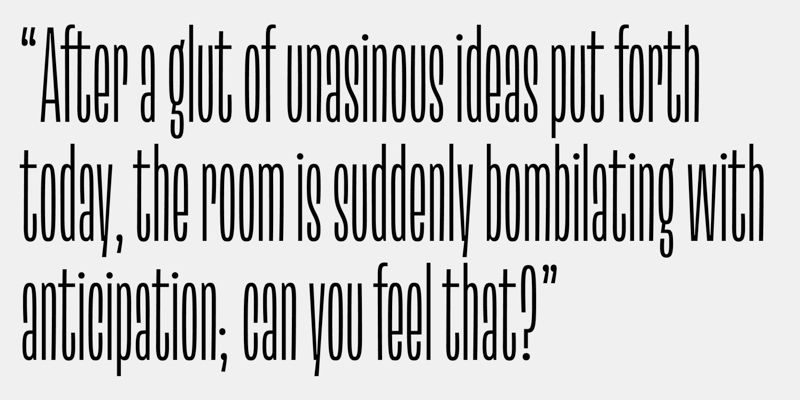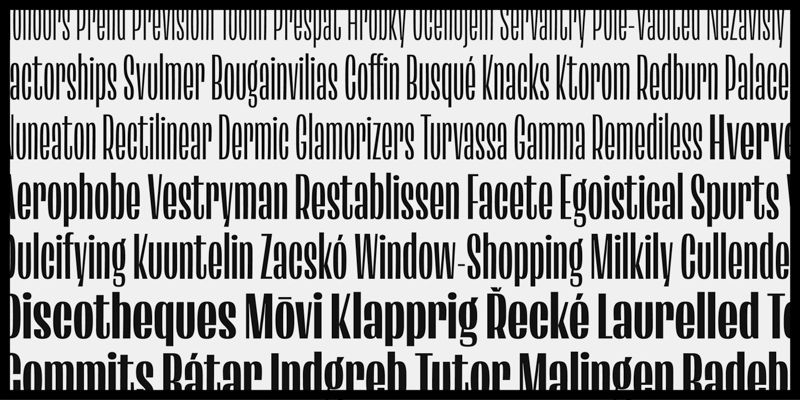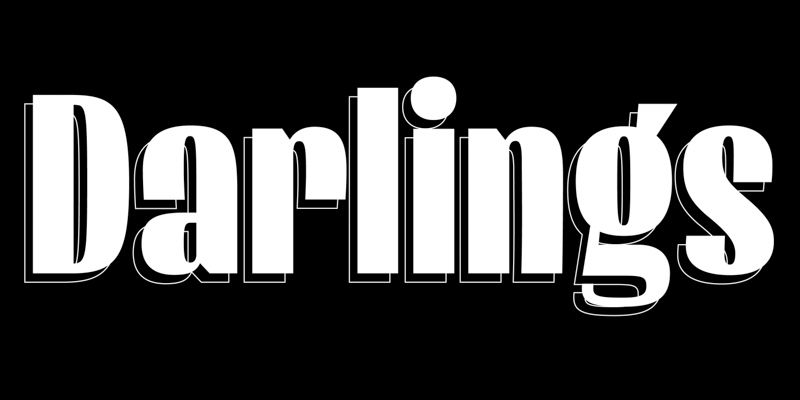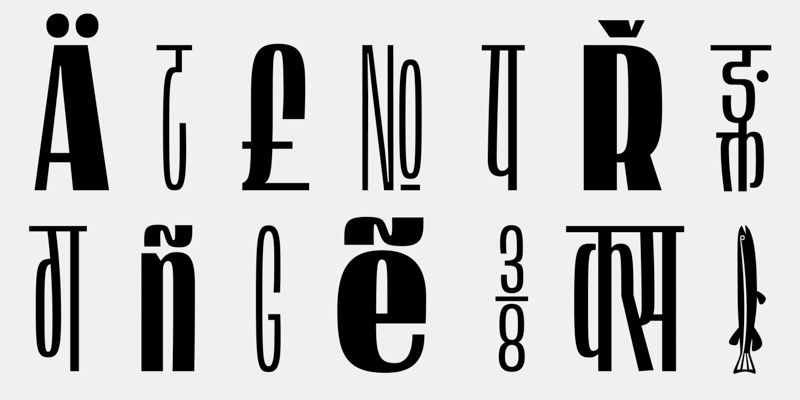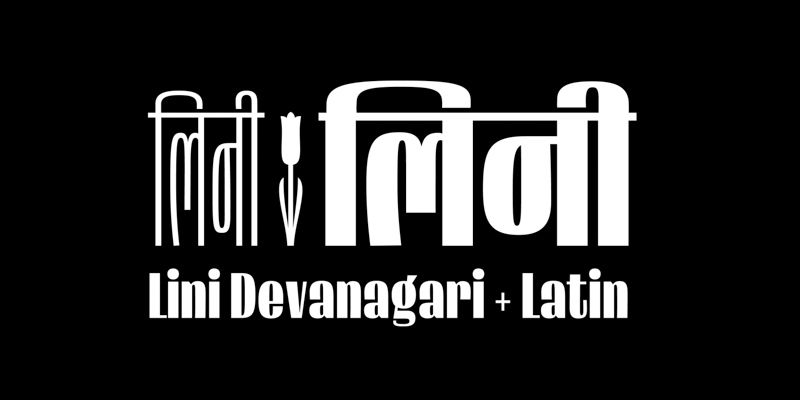
Lini는 데바나가리와 라틴어 스크립트를 위해 폭이 좁게 디자인된 현대적 서체로, 비정상적으로 큰 x-높이와 콤팩트한 상승과 하강이 특징입니다. 수상 경력에 빛나는 이 디자인(Certificate of Typographic Excellence 인증서, Type Directors Club)은 극도의 압축과 놀라운 가독성의 균형을 조화시켜 눈길을 사로잡는 헤드라인과 타이틀을 연출합니다.
5가지 극적으로 다른 굵기로 제공되는 Lini는 최소한의 수평 공간에서 역동적인 타이포그래피 계층 구조를 만드는 강력한 도구입니다. 허리가 낮은 라틴 문자와 최적화된 데바나가리 형태는 압축에도 불구하고 가독성을 유지하여 공간이 제한적이지만 임팩트가 중요한 영화 크레딧부터 그래픽 의류까지 어디에나 이상적입니다.